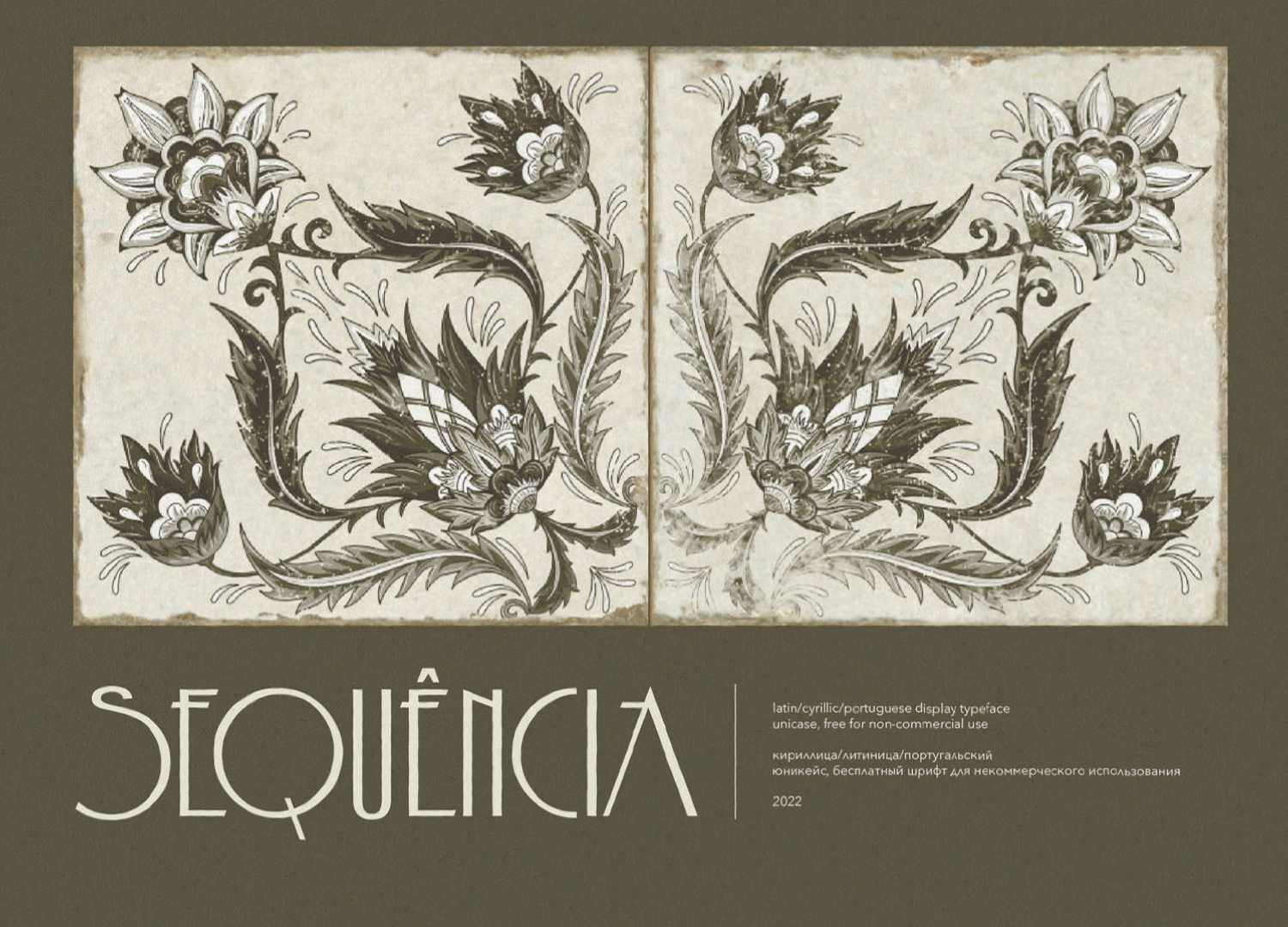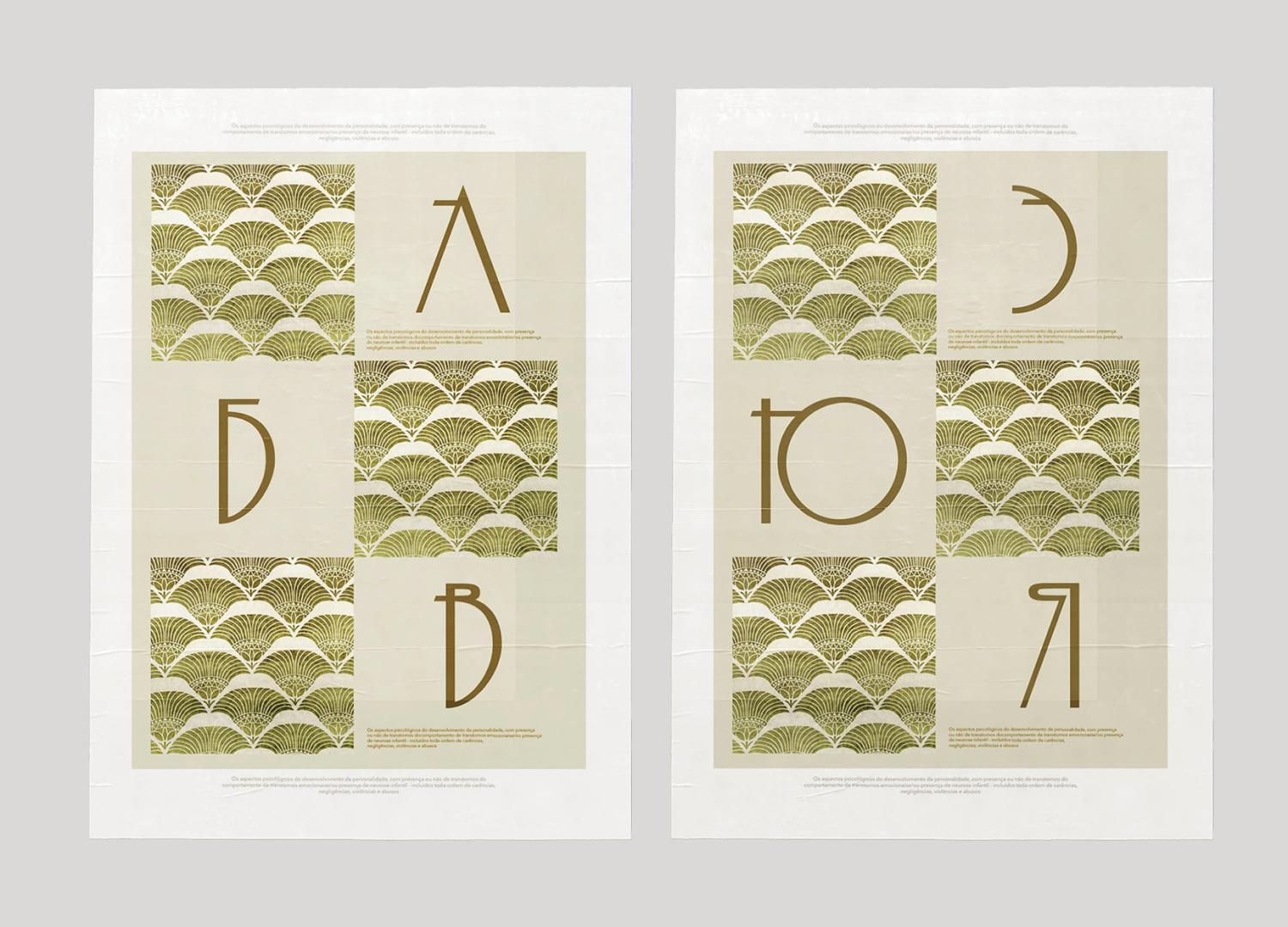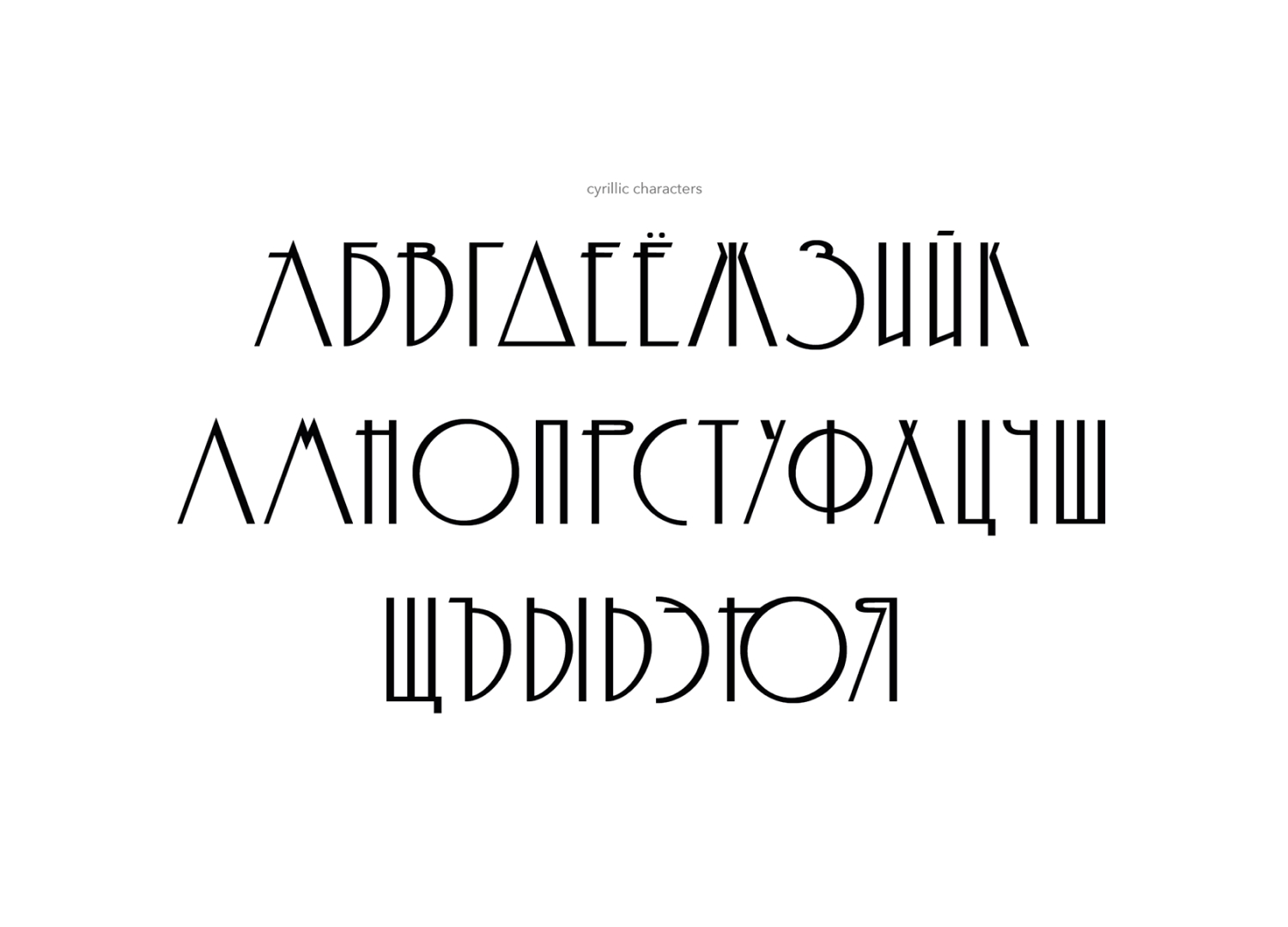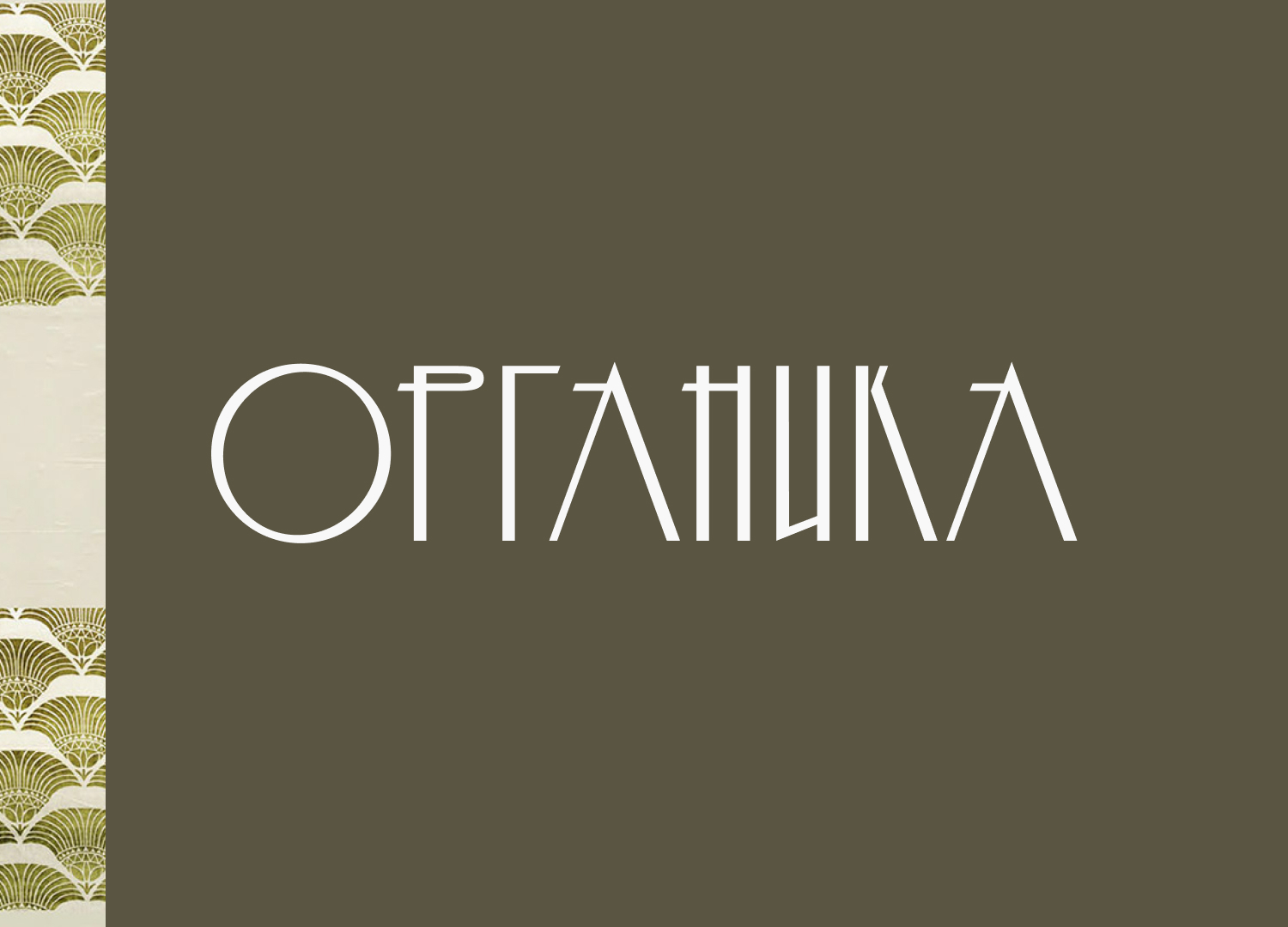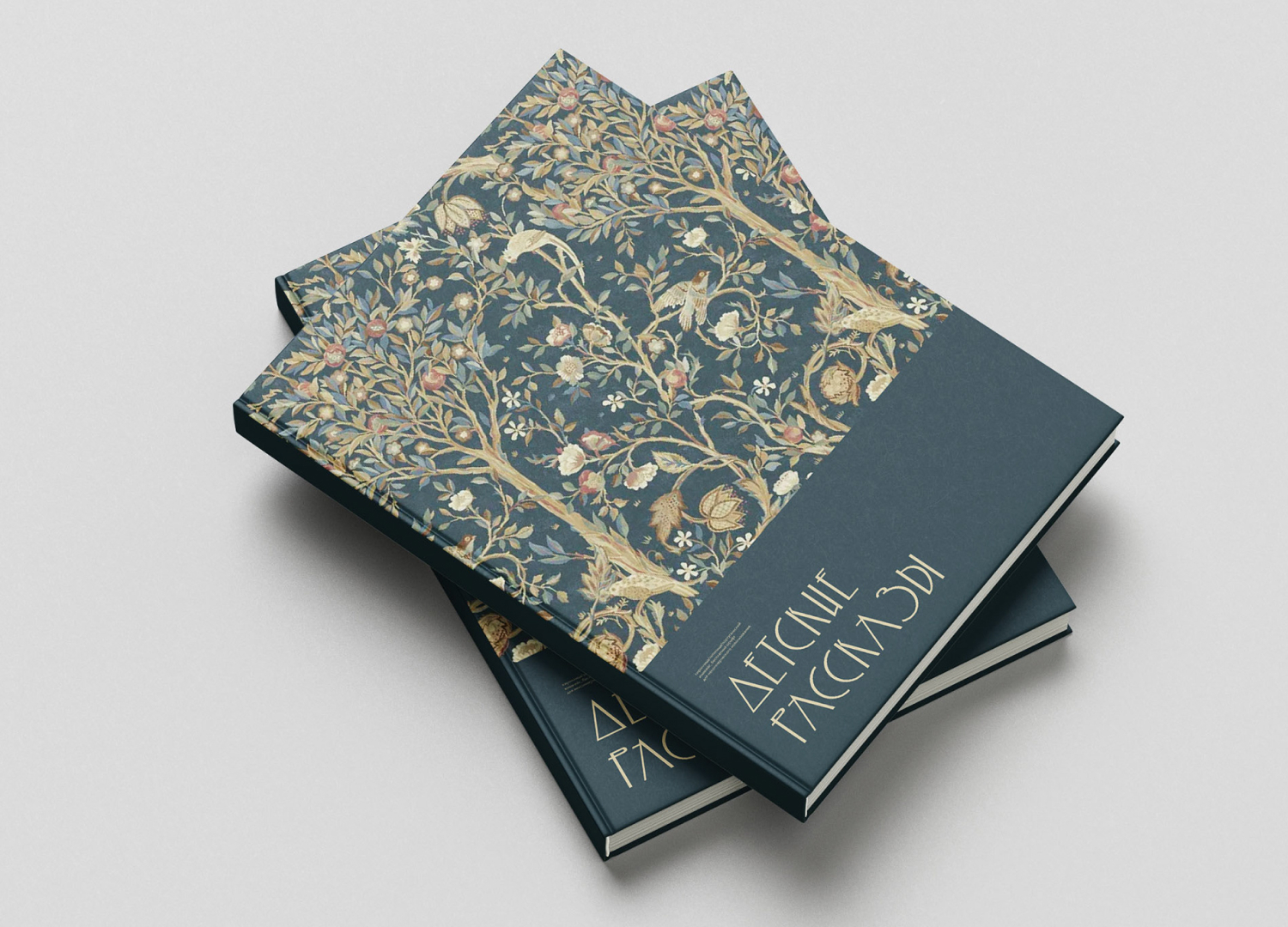
Шрифт Секвенсия
Шрифт Секвенсия.
От автора: «зауженный гротеск для крупного кегля с легким ретро-налетом. Содержит кириллицу, латиницу и португальскую диакритику. Все штрихи внутри букв сильно прижаты к верхней или нижней части глифа. Шрифт хорошо подходит для заголовков и плакатов.»
От меня: «Нихрена не понятный, но очень интересный. Бесплатный только для личного использования. Но мало ли, вы хотите плохому человеку открытку им сделать. Чтобы он сидел и не понимал, что там написано.
Автор: Stanislav Chiganov отличный кстати дизайнер шрифтов. Презентация на 99% сохранена.
Шрифт уходит в категорию странных)